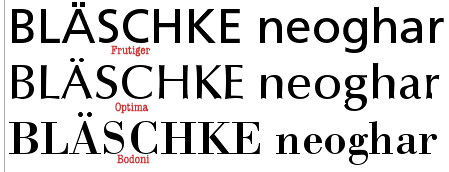
benötige einen Font zum Erstellen von Fließtexten, der mit der Optima (Medium Schnitt) harmoniert. Die Grundschnitte regular/bold sollten auch kursiv verfügbar sein.
Sean Cavanaugh empfiehlt in seinem Buch "TypeDesign", dem eine CD-ROM mit etlichen Fonts beiliegt und das schon von daher ein Kauftipp ist, die Palatino (auf der CD-ROM = URW Palladio) oder die Sabon.
Gibt es auch einen Vorschlag für eine serifenlose Schrift?
schwierig. Formal zu weit weg (Univers, etc.) harmoniert nicht, formal zu nahe verliert sich die Unterscheidbarkeit. Einer Serifenschrift hingegen kann formal ähnlich, aber trotzdem gut unterscheidbar sein.
Was hast du denn mit den beiden Schriften genau vor?
Gibt es auch einen Vorschlag für eine serifenlose Schrift?
Da die Optima eine Schrift zwischen der Frutiger (Serifenlos) und der Bodoni (Klass. Antiqua) ist , würde ich es einmal mit der Frutiger probieren. Es kann natürlich sein, dass sie formal zu ähnlich ist.
Was hast du denn mit den beiden Schriften genau vor?
Sitze als leitender Ingenieur (Nachrichtentechnik) an der schriftlichen Ausarbeitung eines Projektes für einen Neukunden. Habe dabei die Info, daß deren Geschäftsführer zuvor für eine Werbeagentur tätig war. Unsere Geschäftspapiere sind mit Optima Medium erstellt. Jeder hier im Hause nutzt dann analog die Optima auch als Hausschrift. Ich finde dies gerade in diesem Kontext recht langweilig und anspruchslos. Vielleicht läßt sich ja durch diesen Ansatz diesbezüglich etwas bewegen.
Serifenlose Schriften erscheinen mir in technischen Abhandlungen mit einem hohen Anteil an Formeln und Berechnungen informativer. Mir persönlich gefällt die TheSans B sehr gut, bin mir aber nicht sicher, ob das zusammen mit der Optima harmoniert.
harmonie ist etwas sehr subjektives. da spielen viele andere dinge noch eine rolle. für ein ausgewogenes schriftbild, sollte bei schriftmischungen die minuskelhöhe annähernd identisch sein.
ich persönlich finde, dass optima/thesis funktionieren kann.
Vielen Dank für die netten Beiträge. Ich habe mich für die FrutigerNext in den Schnitten Medium und Heavy entschieden. Sie ist für mein Auge noch etwas fließender und hat vorallem klarlinigere Ziffern als die TheSans B.